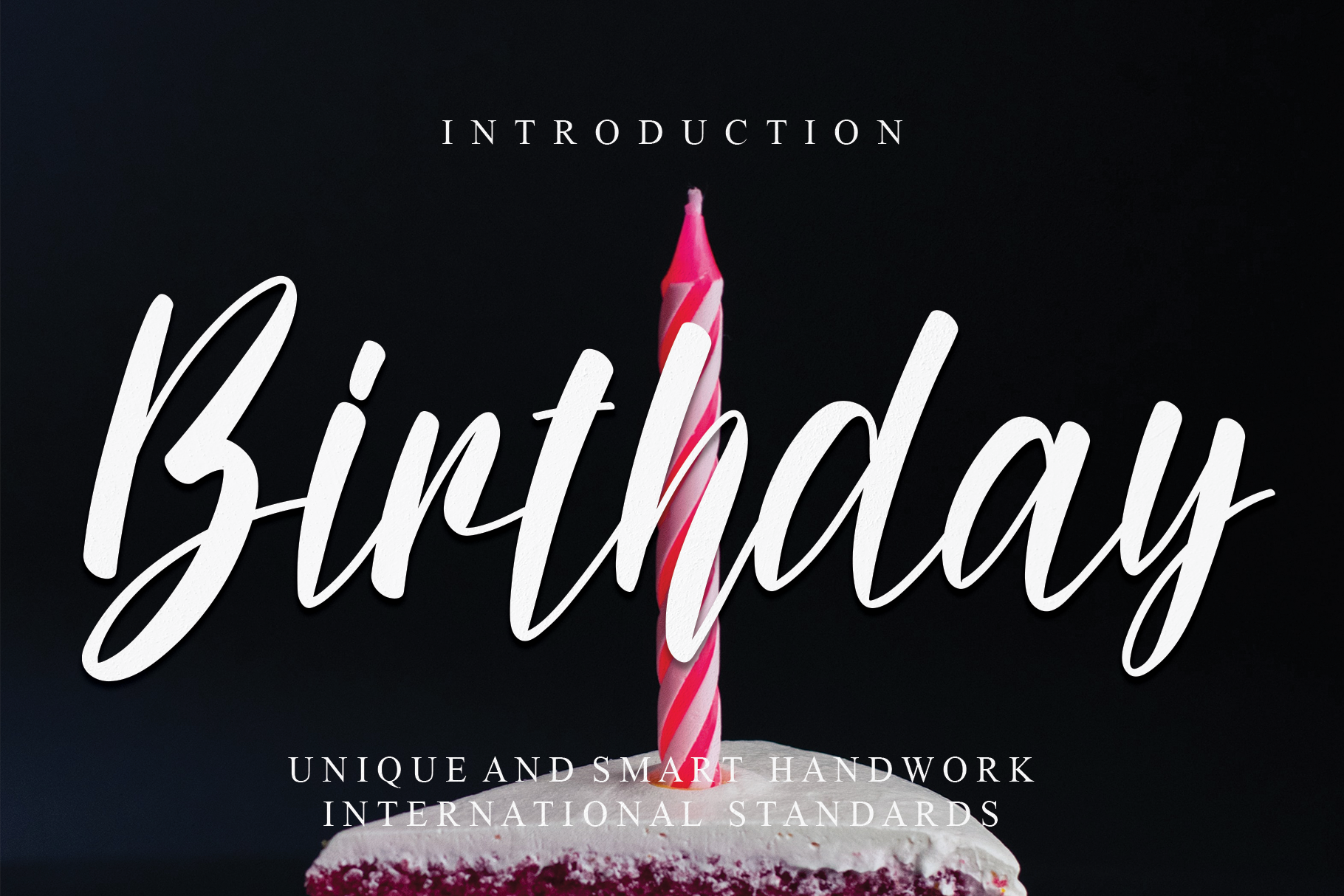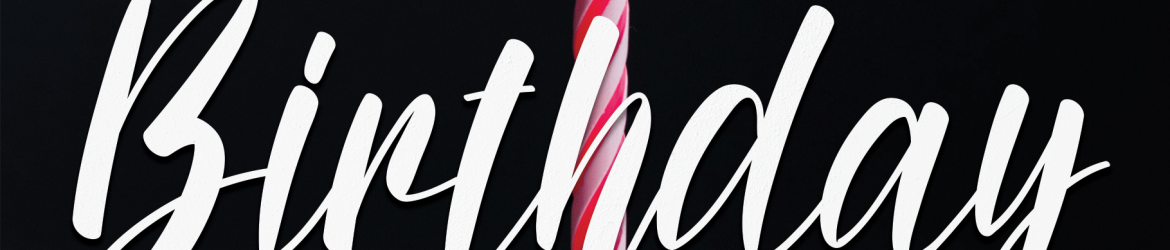
Esta fonte ‘Birthday Font’ é inspirada no estilo clássico do tipoográfico, trazendo seu próprio toque único a qualquer projeto de design. Ideal tanto para projetos digitais como físicos, seja para web, impressão, ou até mesmo imagens em movimento – Birthday será sempre um elemento elegante e visualmente impactante. Desenvolvida pelo designer creativeletter, esta fonte handwritten oferece uma maneira incrível de trazer personalidade a qualquer projeto. Seja você criando uma página de nascimento digital, preparando cartões de aniversário para impressão ou até mesmo gravando um vídeo de felicitações – Birthday ficará à altura do mais exigente dos projetos.